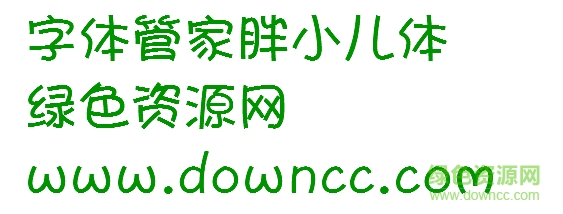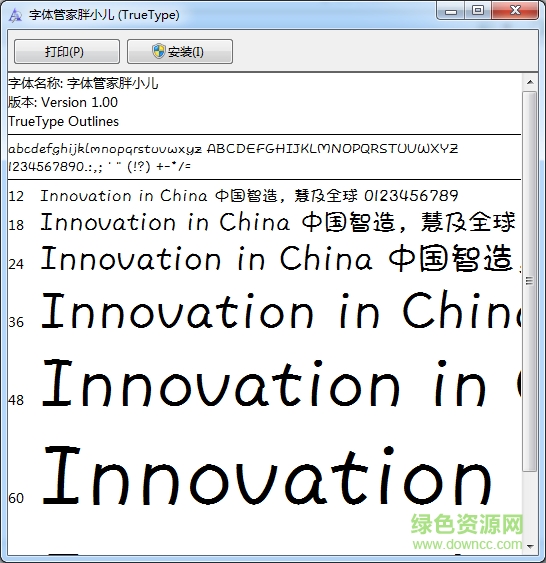
胖小兒字體是字體管家推出的一款童趣卡通字體,筆畫彎曲有型,打破常規(guī)的束縛,更顯稚童的嬌憨可愛,綠色資源網(wǎng)歡迎大家免費(fèi)下載哦!
字體管家胖小兒體是一款兒童卡通風(fēng)格的pop字體,趣味性十足。此款字體適用于POP海報(bào)及兒童廣告展板的設(shè)計(jì)等應(yīng)用。